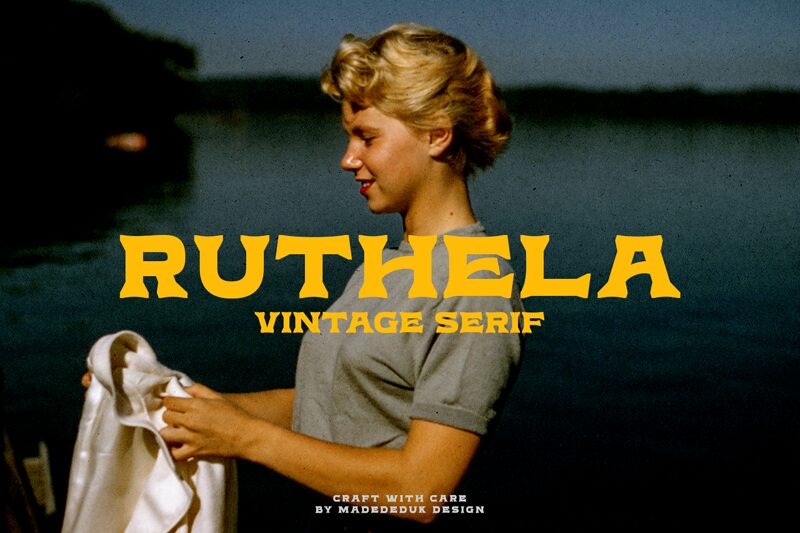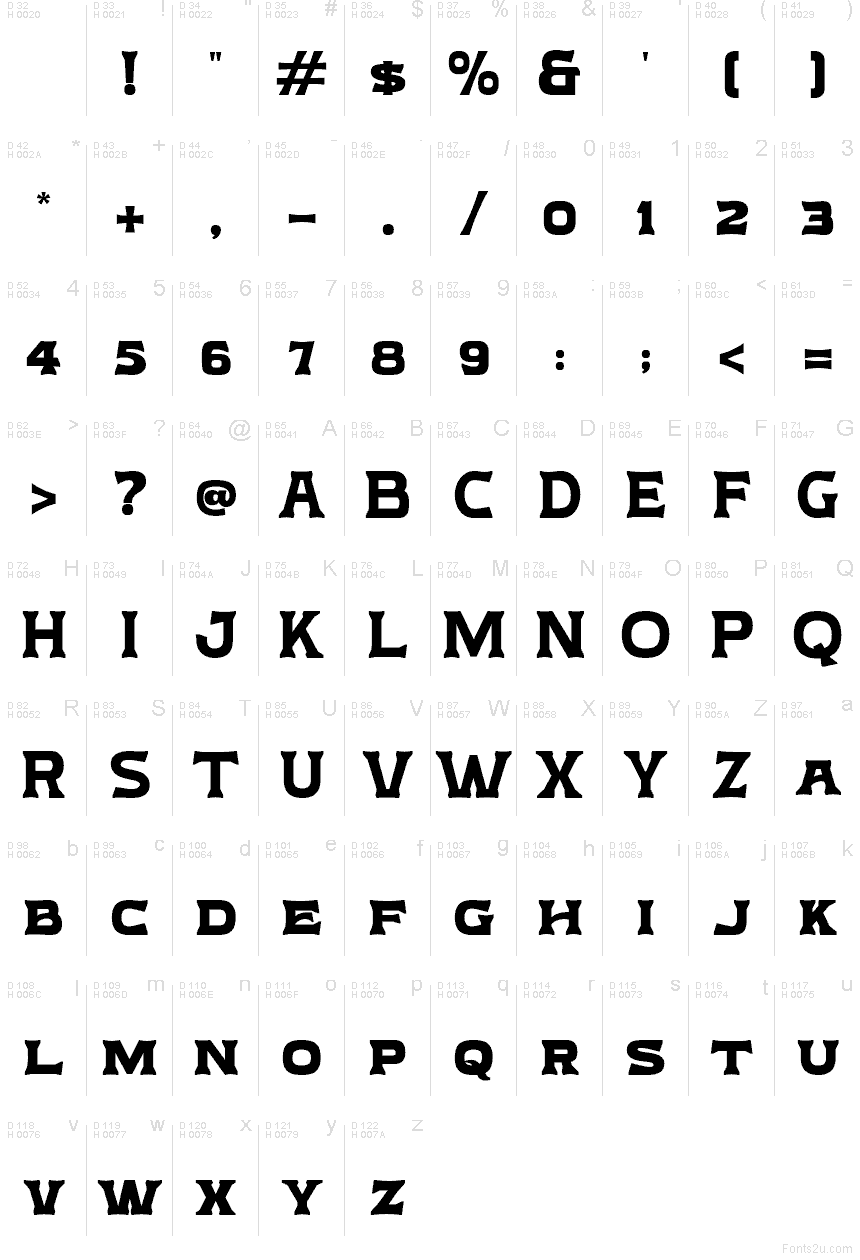
Ruthela DEMO Regular
Ruthela od Suandana Ipandemade je bezplatné retro písmo typu display, ktoré zaujme svojimi širokými, v hornej časti mohutnými tvarmi a ostro rozšírenými koncami, vďaka čomu pôsobia znaky ako vytesané do nápisov. Opakujúce sa klinovité pätky a zaoblené vnútorné krivky dodávajú dizajnu na dôraznosti a troche dramatičnosti, pričom si zachováva svoju profesionálnu úroveň.
Ruthela je tak prirodzenou voľbou pre nadpisy plagátov, obaly albumov, branding barov či kaviarní, obaly produktov a veľké redakčné titulky, kde silueta písma hraje hlavnú rolu. Štvorcový rytmus a výrazné pätky dodávajú krátkym slovám pevnú štruktúru, najmä v layoutoch, ktoré vyžadujú vintage nádych bez toho, aby museli siahnuť po typických skriptových alebo slab serif písmach.